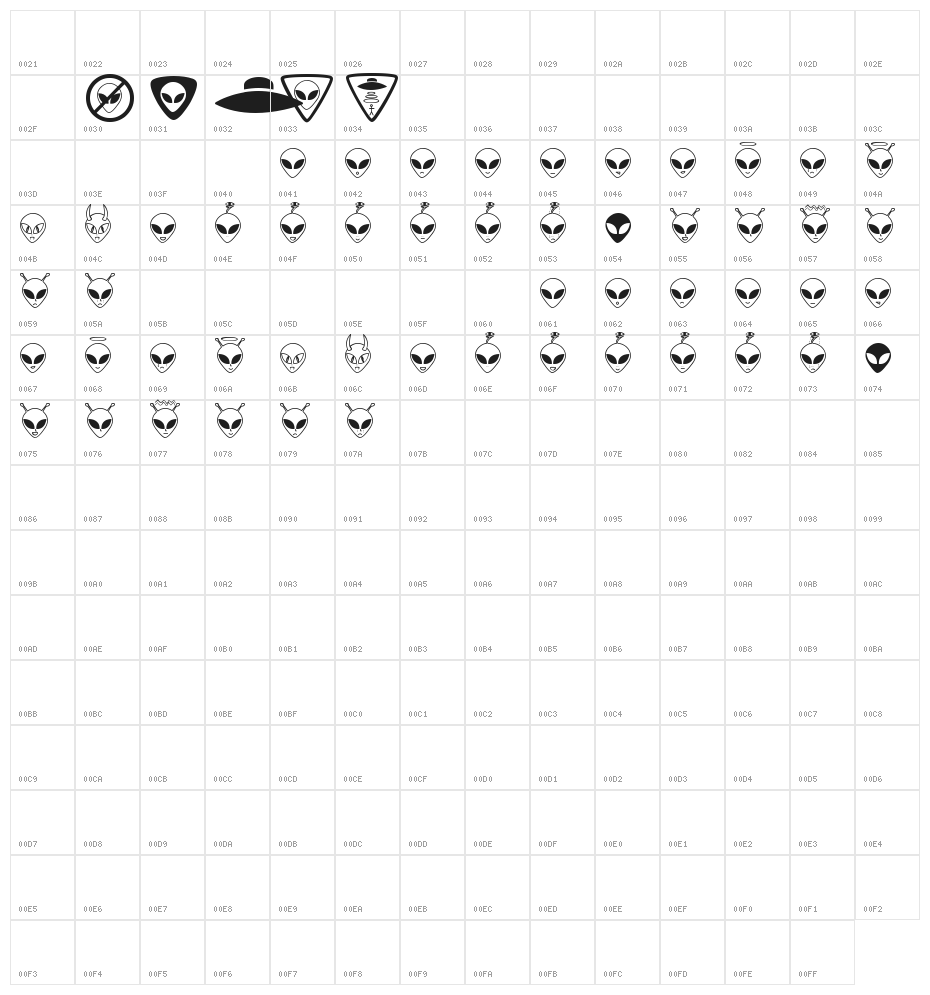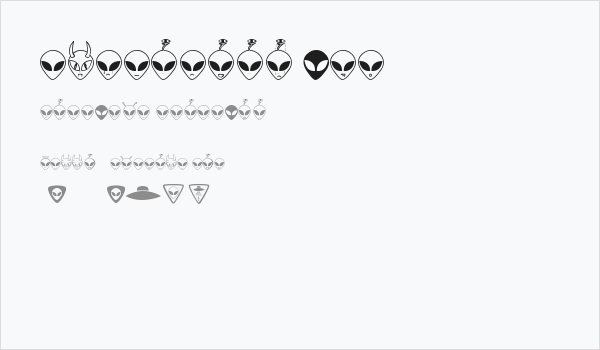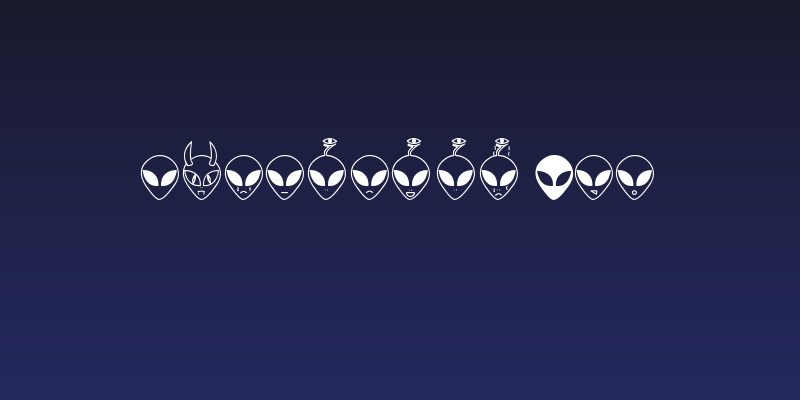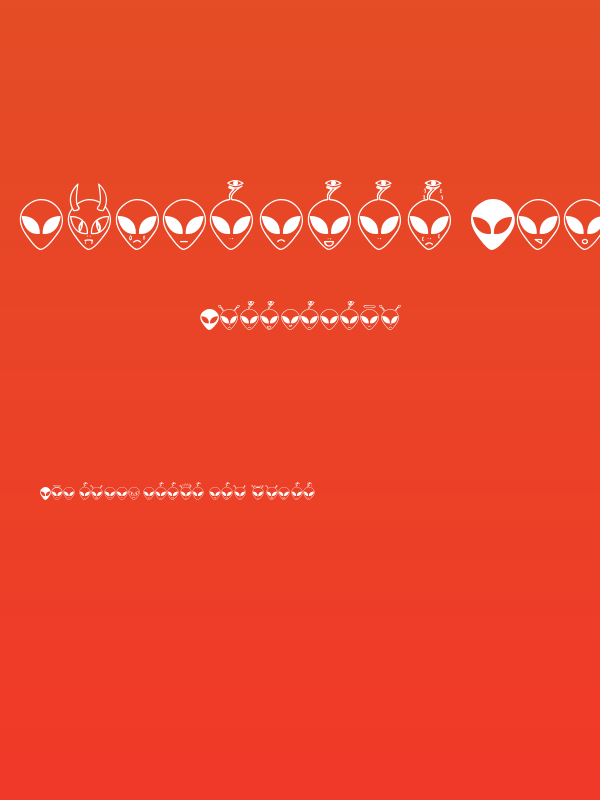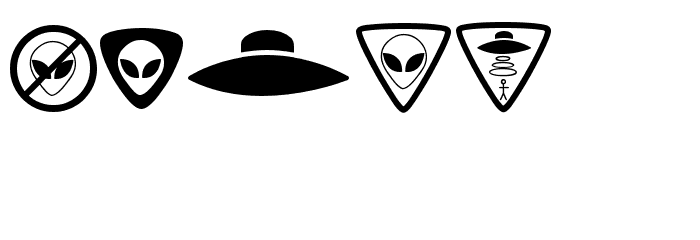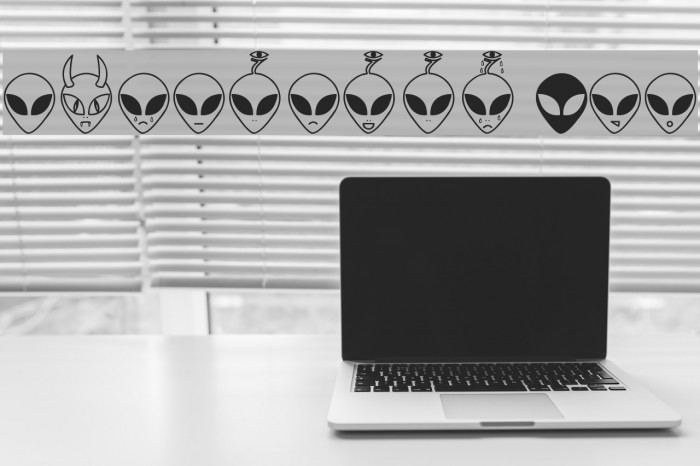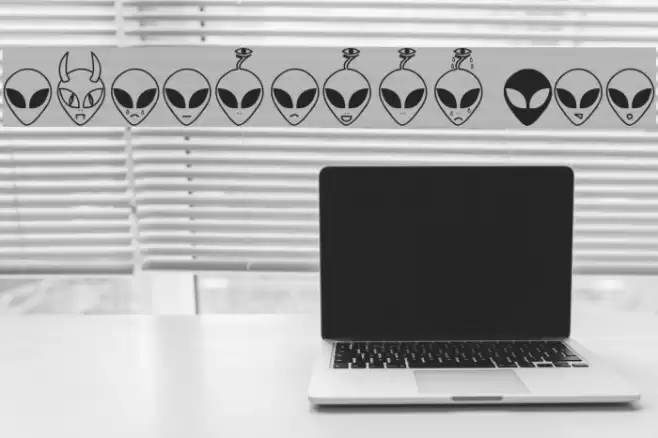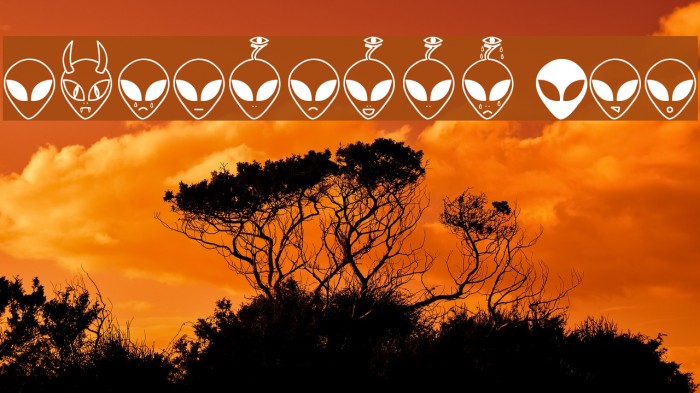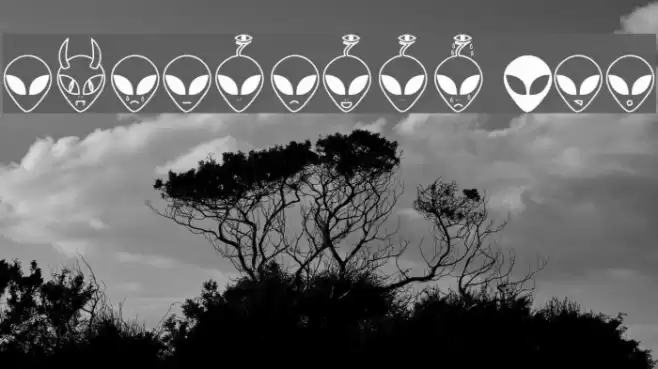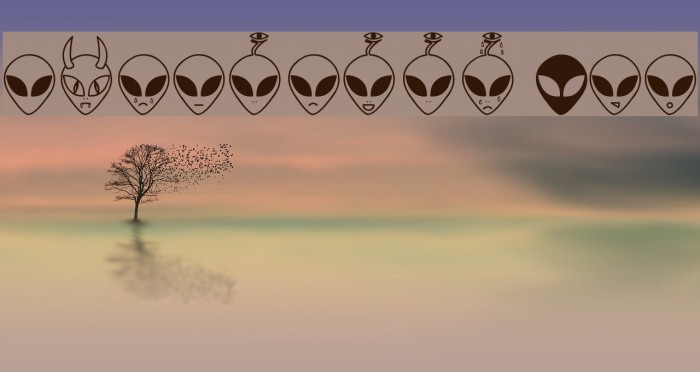
Aliencons TFB Font
✎ Dingbats
| Catégories | Dingbats |
| Cas d'utilisation | Logos, Posters, Merchandise |
| Projets proposés | Ideal for sci-fi themed designs, children's books, game graphics, and novelty merchandise. |